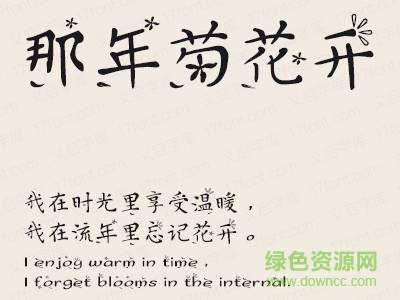
義啟那年菊花開體是一款義啟出品的重陽節(jié)字體,自帶花形,富有韻味,讓大家感嘆離殤。字形優(yōu)雅適合藝術(shù)創(chuàng)作、噴涂等。歡迎大家來綠色資源網(wǎng)踴躍下載義啟字體!
義啟那年菊花開,那年重陽, 迎著明媚的陽光, 窗外的菊花花開正艷, 是誰,在譜寫離別的篇章?我剪一段時光裹住心傷。